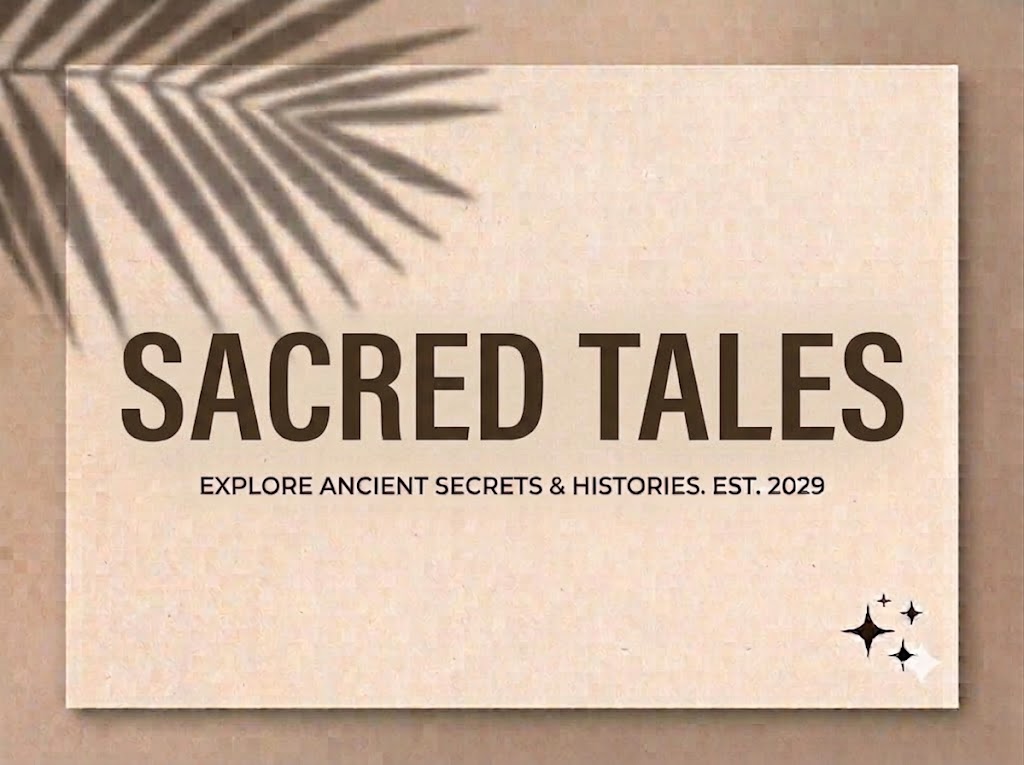
1FTV Clearface Gothic Bold
Trong các ấn phẩm truyền thông hiện đại, một phông chữ tiêu đề có độ dày lớn (Bold) kết hợp cùng phom dáng vững chãi luôn mang lại hiệu quả thị giác tức thì.
Nó giúp nội dung của bạn đập vào mắt người xem ngay từ những giây đầu tiên, tạo điểm nhấn không thể ngó lơ trên các bảng tin kỹ thuật số hay các đoạn video ngắn.
Nếu bạn đang tìm kiếm một bộ font vừa mang nét cổ điển, đáng tin cậy của trường phái gothic truyền thống, vừa giữ được sự gọn gàng, hiện đại thì font 1FTV Clearface Gothic Bold chính là lựa chọn tối ưu.
Giới thiệu về font 1FTV Clearface Gothic Bold
Font 1FTV Clearface Gothic Bold là một bộ chữ thuộc thể loại hiển thị không chân (sans-serif) sở hữu cấu trúc đậm nét, chắc chắn và đầy sức nặng truyền thông.
Phiên bản này được hoàn thiện chuẩn chỉnh ở Version 001.000, mang đến sự nhất quán hoàn hảo cho từng ký tự khi sắp xếp đứng cạnh nhau.
Đặc điểm nổi bật của phong cách thiết kế Clearface Gothic Bold
Sức hút lớn nhất của font 1FTV Clearface Gothic Bold đến từ nét chữ dày dặn, mạnh mẽ nhưng lại ẩn chứa những đường cong tinh tế mang đậm hơi hướng nhân văn (humanist).
Dù là font không chân (sans-serif), các ký tự như a, g, c, e lại có các góc bo tròn và đường vát cong nhẹ rất đặc trưng, tạo cảm giác thân thiện, dễ chịu và có cá tính riêng biệt chứ không hề thô cứng như các dòng font gothic công nghiệp thông thường.
Bộ font hỗ trợ đầy đủ cả hệ thống chữ hoa lẫn chữ thường đồng bộ, giúp bạn tự do sáng tạo và phân tách các tầng nội dung văn bản một cách mượt mà từ tiêu đề chính cho đến tiêu đề phụ.
Để phông chữ vận hành hoàn hảo trên mọi phần mềm, phiên bản font 1FTV Clearface Gothic Bold đã được tối ưu hóa kỹ lưỡng về các thông số kỹ thuật nội tại.
Hệ thống khoảng cách chữ (kerning) và độ giãn dòng đã được căn chỉnh chuẩn xác, giúp các từ khi đứng cạnh nhau luôn đạt tỷ lệ vàng về mặt khoảng trống, không bị dính nét hay gây ngột ngạt cho người đọc.
Bên cạnh hệ thống chữ cái hoa và thường đồng bộ, phông chữ còn tích hợp đầy đủ dãy số từ 0-9 cùng hệ thống ký tự đặc biệt, dấu câu thông dụng (1234567890.:,;'"(!?)+-*/=). Bản Việt hóa chuẩn chỉnh này đảm bảo bạn gõ tiếng Việt hoàn toàn mượt mọc, không lo bị nhảy font hay lỗi hiển thị dấu câu khó chịu.
Hình ảnh demo thực tế của font 1FTV Clearface Gothic Bold
Để giúp bạn dễ dàng hình dung khả năng hiển thị đa dạng của phông chữ này trên các kích thước khác nhau, hãy cùng xem qua bảng mô phỏng từ file hệ thống
Kích thước nhỏ (12pt – 24pt): Nhờ cấu trúc chữ thông thoáng, các nét chữ đậm và bộ chữ thường vẫn hiển thị rõ ràng, ngay ngắn, cực kỳ dễ đọc trên màn hình điện thoại di động.
Kích thước lớn (36pt – 72pt): Đây là đất diễn hoàn hảo nhất để font chữ phô diễn sức nặng hình khối và các đường cong tinh tế, tạo tác động thị giác mạnh mẽ cho các tiêu đề chính.
Ứng dụng của font Clearface Gothic Bold trong thiết kế đồ họa và làm video
Sở hữu nét cá tính mạnh mẽ, vững chãi và cấu trúc hoa – thường linh hoạt, font 1FTV Clearface Gothic Bold mở ra không gian ứng dụng rộng lớn cho các dự án thiết kế truyền thông:
Làm tiêu đề video ngắn (TikTok, Reels, Shorts): Dáng chữ đậm, rõ ràng cực kỳ nổi bật trên các khung hình đứng 9:16, giúp các câu giật tít, từ khóa chính thu hút người xem ngay lập tức khi lướt feed.
Thiết kế ảnh thu nhỏ YouTube (Thumbnail): Đây là vũ khí tuyệt vời cho các video thuộc chủ đề chia sẻ kiến thức, nội dung quảng cáo, review công nghệ hoặc kinh doanh để tăng tỷ lệ nhấp chuột nhờ độ dễ đọc cực cao từ khoảng cách xa.
Banner và poster quảng cáo sự kiện: Hoàn hảo cho các poster giới thiệu sản phẩm, banner chương trình ưu đãi, hoặc các ấn phẩm truyền thông đòi hỏi sự chắc chắn, đáng tin cậy và chuyên nghiệp.
Nhận diện thương hiệu tối giản: Phù hợp làm logo dạng chữ khối, biểu ngữ quảng cáo hoặc thiết kế nhãn mác cho các thương hiệu local brand thời trang, kỹ thuật hoặc các studio sáng tạo hiện đại.